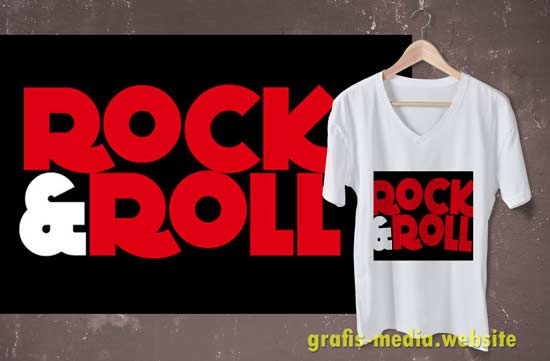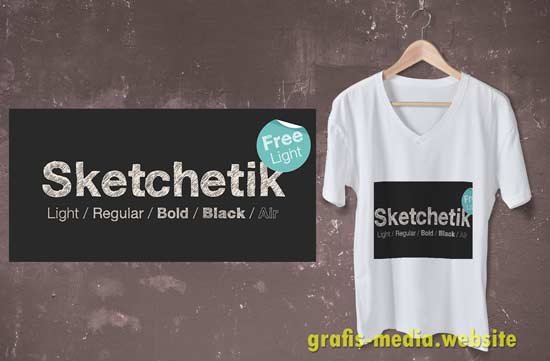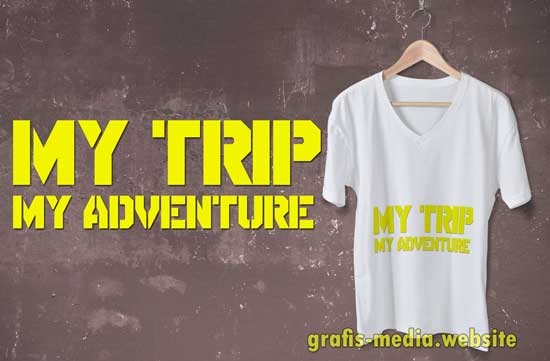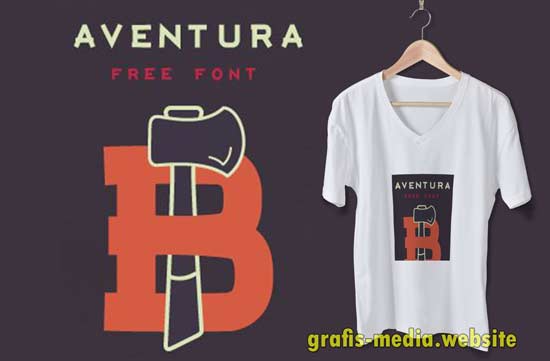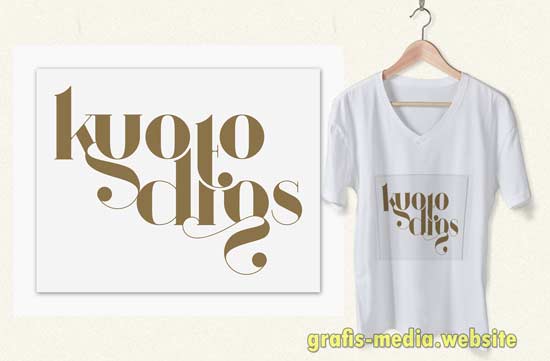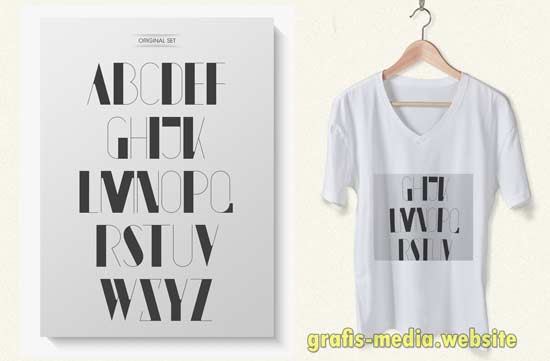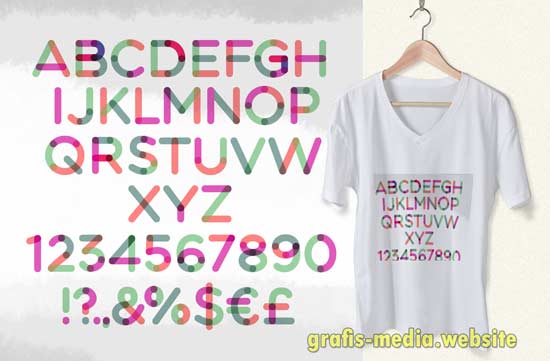
15 Font Keren Untuk Desain Baju Kaos Distro
Dalam membuat desain baju distro, pasti membutuhkan kreativitas tinggi. Karena konsumen selalu ingin sesuatu yang berbeda. Jangan gunakan desain monotone “hanya itu-itu saja”. Kalau perlu buatlah desain unik yang belum pernah ada sama sekali. Ini adalah salah satu cara jitu, agar baju distro sobat cepat lakunya.
Sebagai bahan penunjang desain, maka kita juga memerlukan Font untuk menambah kesan pada baju distro. berikan font yang berbeda-beda sesuai tema. caranya update terus font terbaru setiap hari, agar desain baju ikut terupdate.
1. Font My Trip My Aadventure | Download
Siapa yang tidak pernah melihat tulisan “My Trip My Adventure”.  Salah satu slogan bagi yang berjiwa petualang. Bagi yang ingin tahu, apa nama font distro yang digunakan pada my trip my adventure maka saya akan memberiktahukannya.
Nama Font yang digunakan My trip my adventure adalah Disparador Stencil. font ini menjadi bahan diskusi bagi sebagian orang. soalnya banyak yang penasaran.
Font my trip my adventue
2. Sketchetik | Download
Bentuk dari font distro sketchtik memiliki arsiran didalamnya jadi seolah seperti huruf sketsa. sangat cocok untuk baju kalangan anak arsitek, desainer, drafter dan hobby seni. kalau pakai font ini pasti akan banyak pembeli berdatangan ke outlet sobat.
3. Accent | Download
Kelebihan dari font distro accent adalah bentuknya yang slim/kurus. membuatnya terlihat elegan dan stylish. menurut saya, pas untuk desain baju cewe karena kesannya feminim. walaupun cuma kalimat, pasti tetap menghasilkan keindahan. dijamin 100%.
4. Kilogram | Download
Untuk yang berjiwa Rock n Roll, font kilogram bisa jadi pilihan. desainnya yang tebal dan bentuknya unik tapi terbatas. cocok untuk desain baju kalangan remaja.
5. Bobber Free Typecafe | Download
Font distro klasik namun minimalis ini juga favorit saya. bentuknya tidak akan pernah mati ditelan zaman, akan selalu menarik jika dilihat.
6. Blenda | Download
Font distro bergaya elegant ini mampu membuat baju kelihatan lebih artistik. gaya tulisan bersambung pada huruf kecilnya membuatnya terlihat indah.
7. Metropolis 1920 | Download
Font distro untuk desain kaos bertemakan retro atau tempo dulu. walaupun karakter desain retro itu tahun 70-an namun sampai sekarang masih tetap teratas. font bernuansa retro bernama “metroppolis 1920” mampu menciptakan suasan jadul. cocok bagi kalangan dewasa, apalagi 30+ pasti sudah terbiasa dan senang melihat desain seperti ini.
8. Font Book / Publishing House | Download
Font dengan bentuk kumpulan garis, bentuknya yang hanya memperlihatkan edges. kalau mau baju distro kalian bergaya minimalist font book sangat disarankan. walaupun tulisan sudah bisa dibaca, namun tetap masih ada ruang kosong ditengahnya. jadi warna baju masih tetap kelihatan dan menyatu dengan tulisan.
9. Font Aventura | Download
Fon distro aventura, lebih ke jiwa pria. karena asal katanya adalah adventure. model dari setiap hurufnya menonjolkan kejantanan dan dominan siku.
10. CHE’s Bone | Download
11. Font Argoe | Download
12. Multicolore | Download
Font distro warna warni ini terbantuk dari 3 warna. kombinasi warna tersebut sudah bisa memberikan cirikhas pada tulisan kalau di transformasikan kedalam baju kaos.
13. Kaiju | Download
Font kaiju adalah font distro yang memiliki karakter sendiri. sebagian dari bentuk huruf memiliki ketebalan dan lainnya tidak atau kurus. kalau menulis sesuatu, hasilnya akan memperlihatkan kumpulan balok persegi panjang.
14. INTRO | Download
Salah satu kelebihan dari font intro adalah ditengahnya terdapat garis.
15. Lullaby | Download